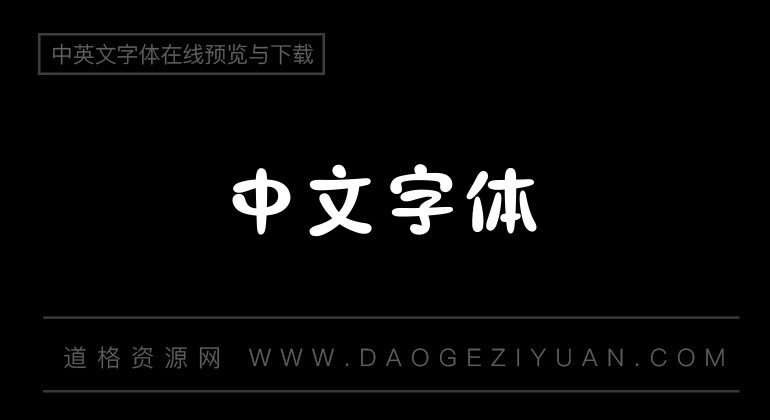
本墨悠圆
本墨悠圆是由国内著名字体设计师梁佳杰设计的一款汉字字体,其设计灵感来源于“悠然见南山”的古典文学,以及“本色”的中国书法笔墨。本墨悠圆的字体体现出传统文化的精髓,具有良好的视觉效果,特别适合用于报纸、杂志、书籍等出版物的排版。本墨悠圆字体具有良好的可读性和可扩展性,可以在各种分辨率的显示器上清晰地显示文字,使文字更加清晰、美观。
本墨悠圆是一款非常不错的手写艺术字体,具有很好的视觉感,适合于文化类的宣传设计、商业类品牌的广告和产品包装设计以及个性化文字排版等较多场景。